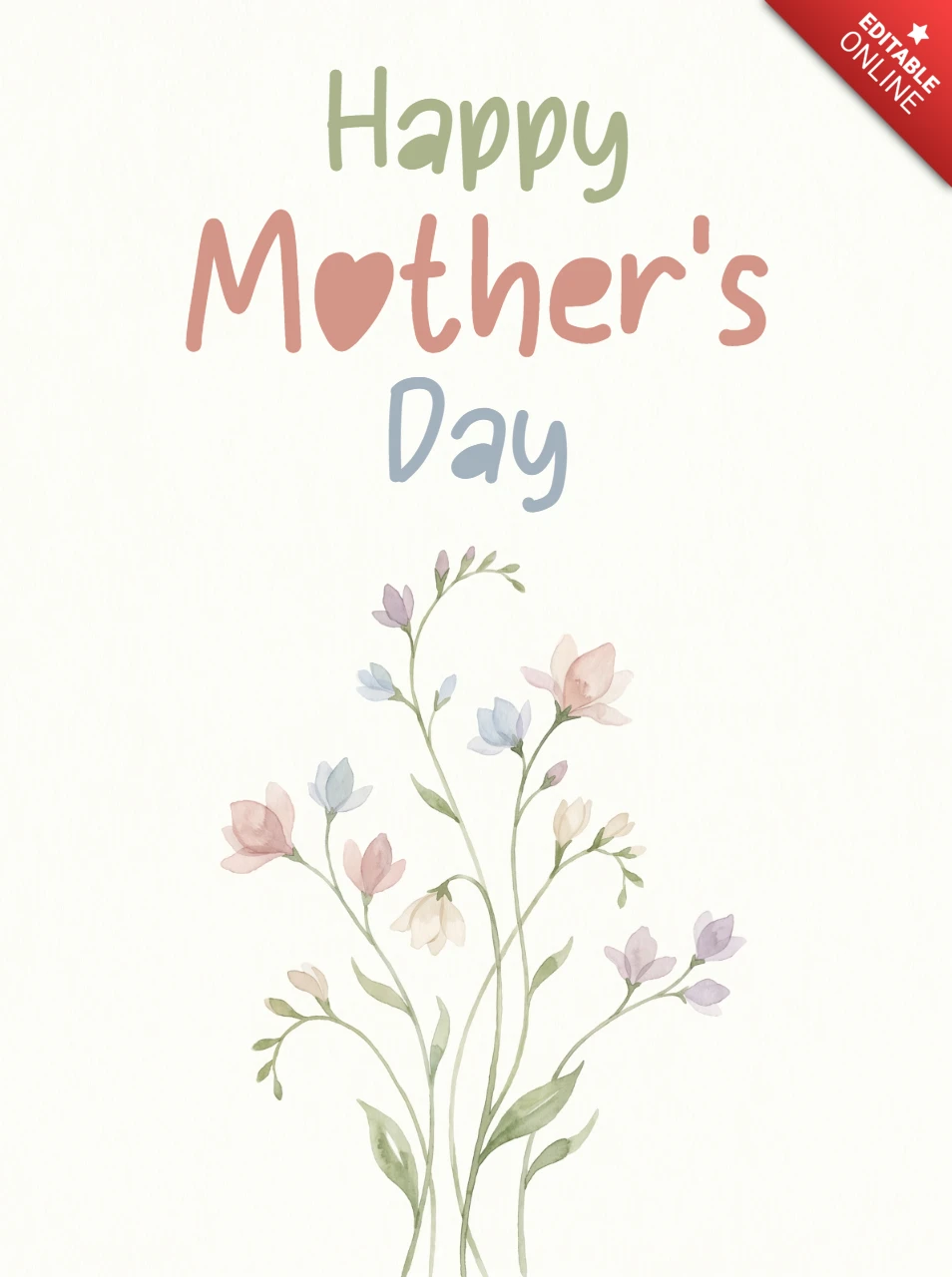
Carte de vœux pour la fête des mères avec des polices colorées, une typographie en forme de cœur et une œuvre florale aquarelle pastel.
Éditer dans Design Studio Télécharger en JPGCélébrez la fête des mères avec notre délicat modèle botanique, présentant des illustrations florales en aquarelle pastel et une élégante calligraphie manuscrite pour un design de carte de vœux minimaliste et coloré.